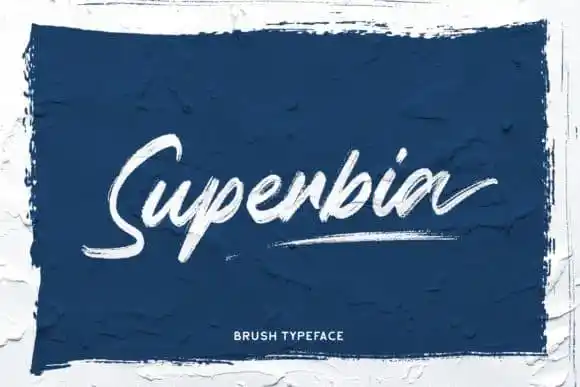
Superbia Brush Font – Download Grátis
A Superbia Brush Font é uma tipografia feita à mão, criada pelo designer Rillatype, que destaca-se com seus acabamentos chamativos produzidos através do uso de um canivete gráfico. Esse tipo especializado em script é perfeito para diversas tarefas de design como criação de marcas, logotipos, posts nas mídias sociais, anúncios e até mesmo embalagens de produtos. O seu charme distintivo e a facilidade com que se integra à variedade de projetos tornam a Superbia Brush Font uma escolha ideal para qualquer trabalho gráfico que precise de uma personalização atraente e moderna.